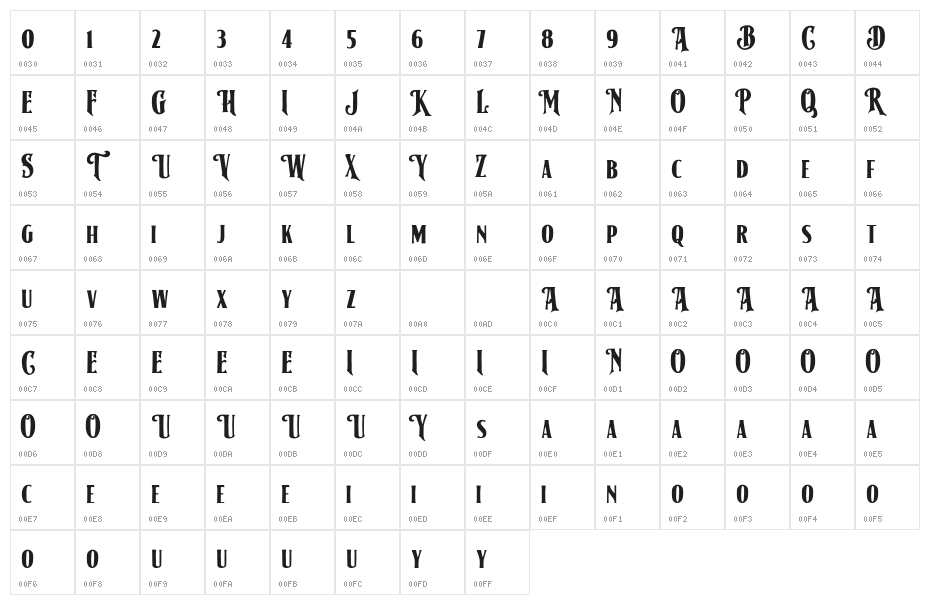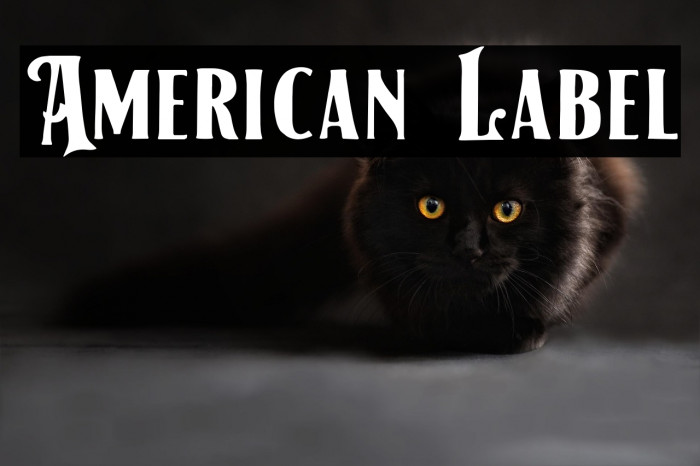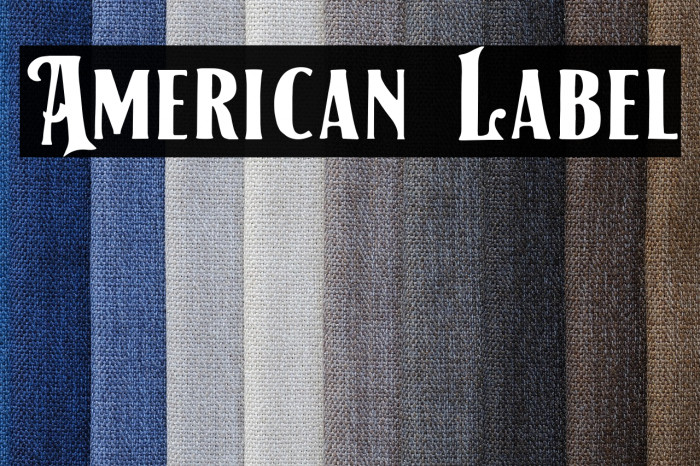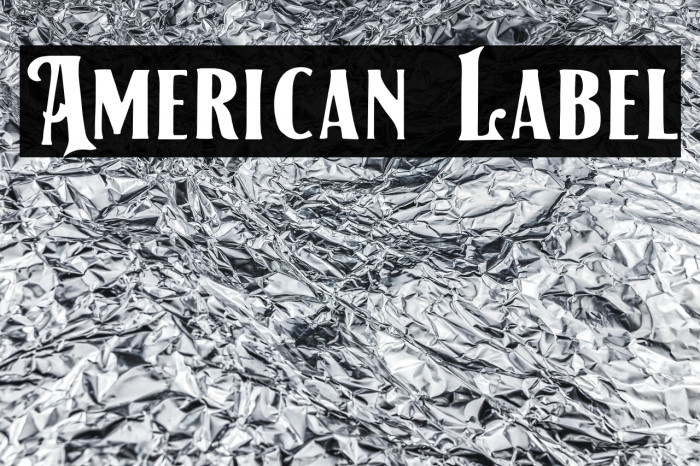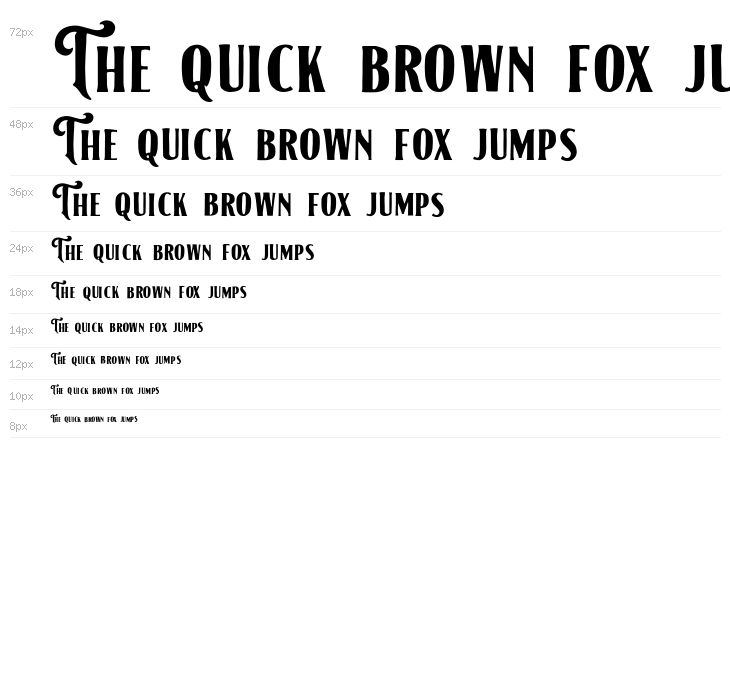
American Label Font
| النمط العام | Vintage |
| مشاريع مقترحة | Ideal for branding, posters, signage, and any project needing a vintage or decorative touch. |